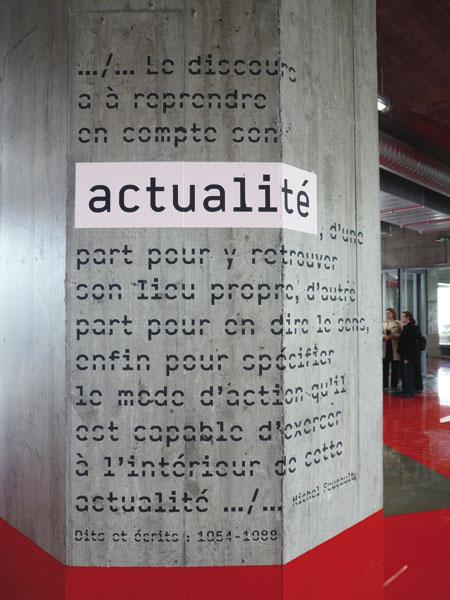
Industrielle Serifenlose aus Leitsystem einer öfftl. Bibliothek (Straßburg)
Danke für die Tipps, lieber Robert. Auf identifont.com war ich schon letzte Woche -- und ärgerte mich, dass ich nichts fand. Dass es etwas Schweizerisches war, lag auf der Hand. Mir gefällt die kühle, eben typisch eidgenössische Sachlichkeit der Deck sehr. Das kleine "a" mit waagerechtem Überlauf verleiht der Schrift einen grundsoliden Charakter. Trotzdem hat sie etwas Rohes, fast Unfertiges. Wäre sie noch verfügbar, hätte ich mir gern ein paar Schnitte zugelegt, vielleicht sogar die ganze Familie.
Kann ich verstehen, coole Schrift.
Etwas Ähnliches im weiteren Sinne aus der Schweiz:
und die Excellent von https://lineto.com
Aber die oben verlinkte PF DIN Mono kommt bis jetzt wohl noch am ehesten ran.